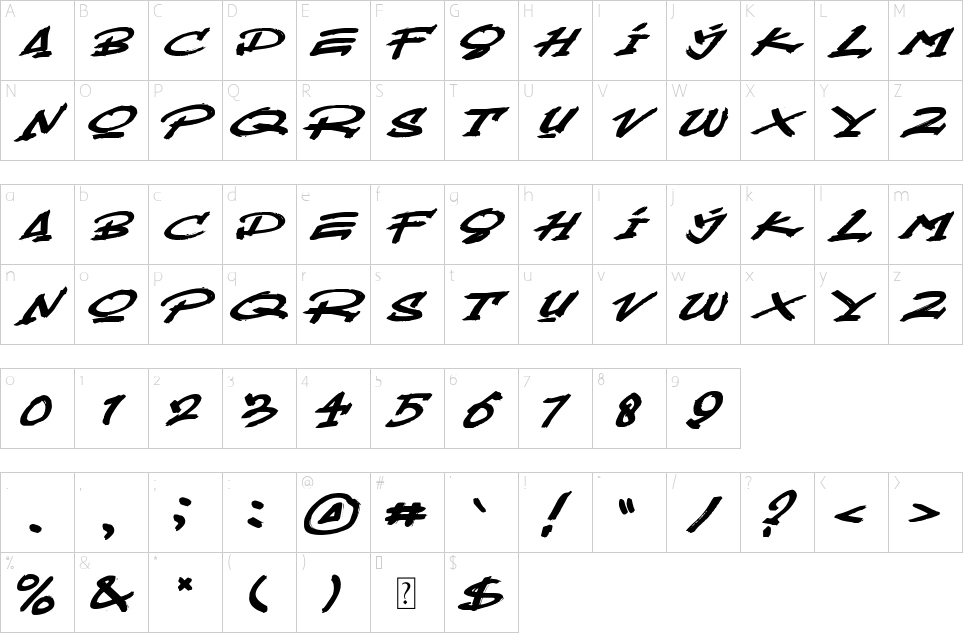
Descubra a elegância e a sutileza em Must Brow, uma fonte livre disponível para download. Ideal para estilos de design que valorizam a simplicidade e a sofisticação, essa fonte foi criada por Font Kong e tem se destacado pela sua praticidade e qualidade. Com uma elegância natural e uma aparência atraente, a Must Brow é perfeita para criar designs profissionais que transmitam confiança e atencioso cuidado. Seja para nomes de produtos, artigos de moda ou até mesmo para o layout de um site, a Must Brow trará um toque diferenciado a qualquer projeto. Recentemente, a fonte foi baixada por 3.138 usuários, demonstrando seu valor e popularidade. Se você está procurando por uma fonte que seja tanto uma opção funcional quanto uma peça de design, a Must Brow é definitivamente um elemento a ser considerado.